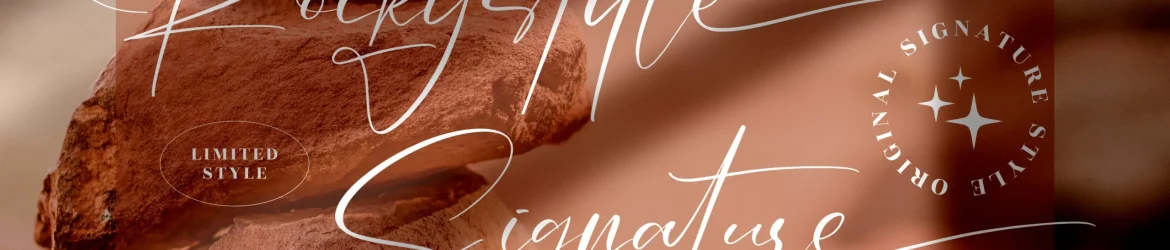
Rockystyle Signature Font – Download Grátis
A Rockystyle Signature Font é uma elegante fonte para assinatura da Perspectype Studio, projetada para dar ao seu projeto aquele toque diferenciado que você merece. Seja ela um projeto de logotipo para marcas, ou um design de embalagem sofisticado; seja mesmo um quote para sua loja online, ou uma lembrança personalizada de aniversário para sua família e amigos, a Rockystyle Signature Font certamente vai complementar seu trabalho. A fonte é perfeitamente adequada para qualquer projeto que exige um toque de luxo, oferecendo você uma opção elegante para expressar sua personalidade e marca. Essa fonte não apenas tornará seus designs mais atraentes, mas também garantirá que eles se destacam no mercado, mantendo sempre aquela qualidade premium que faz das suas criações verdadeiras obras de arte.